Печатная проба колонтитулов: как проверить рукописный шрифт на повторяющихся строках
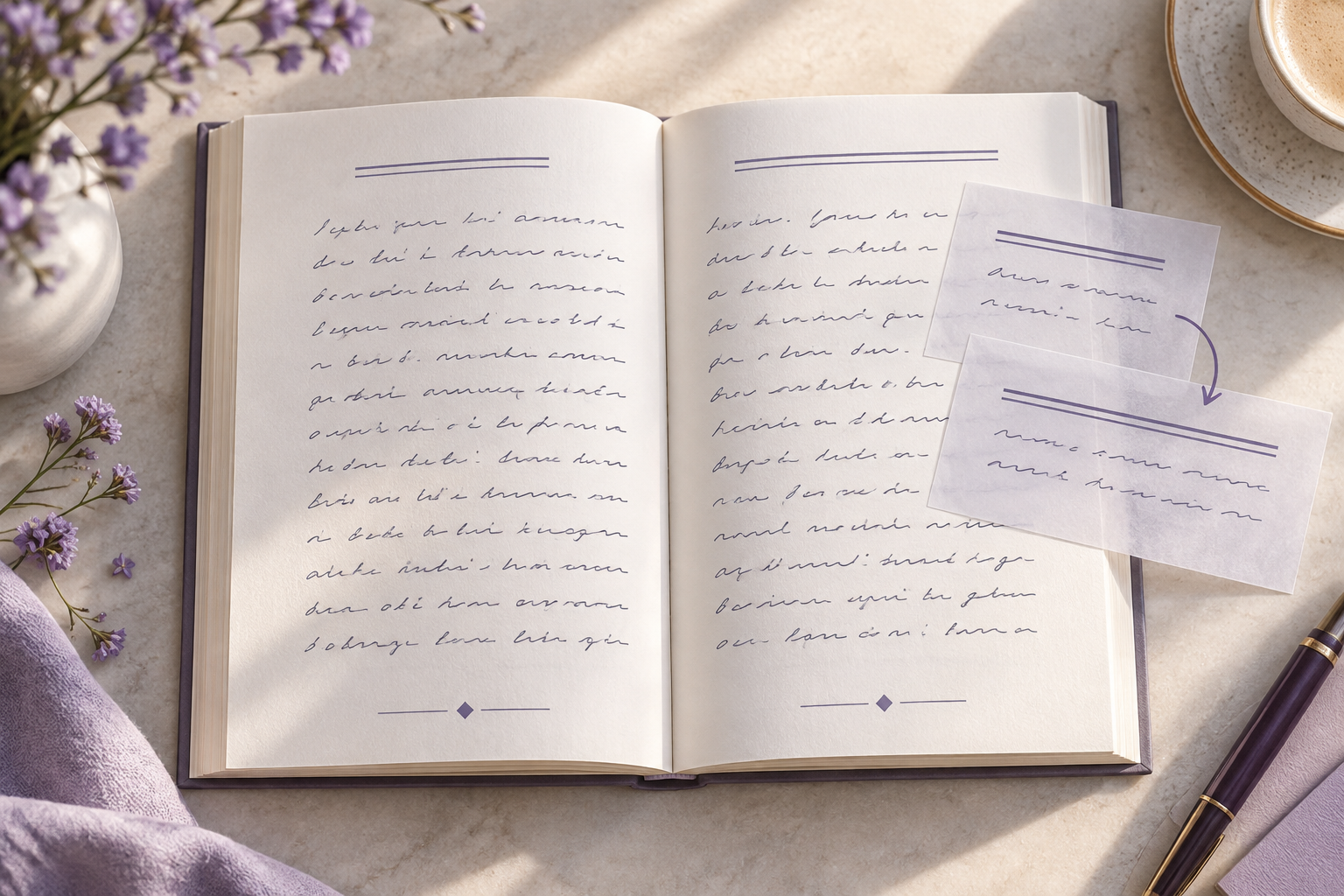
Печатная проба колонтитулов показывает, остаются ли повторяющиеся заголовки и номера страниц заметными, ровными и ненавязчивыми в настоящем книжном развороте. Для проверки нужен не один красивый лист, а короткая последовательность страниц: с длинным и коротким названием главы, сменой чётной и нечётной полосы, переносом и несколькими вариантами номера. Так видно, не теряется ли навигация и не начинает ли шрифт спорить с основным текстом.
Почему колонтитул требует отдельной пробы
Колонтитул — повторяющаяся строка в верхнем или нижнем поле страницы. В нём могут стоять название книги, имя автора, текущая глава или раздел; номер страницы обычно называют колонцифрой. Эти элементы малы и встречаются много раз, поэтому их оценивают не как отдельную надпись, а как часть ритма издания. На экране один заголовок может выглядеть аккуратно, но в серии страниц его ширина, отступы и плотность начинают заметно колебаться.
У рукописного шрифта к этому добавляется неповторимость рисунка. Широкие буквы могут приближаться к внутреннему полю, узкие — оставлять вокруг себя непривычно много воздуха, а росчерки и выносные элементы иногда приближаются к верхней границе. Если набрать один и тот же колонтитул в обычном шрифте-заполнителе, а затем заменить его рукописным, длина строки и зрительный центр могут измениться. Макет при этом формально остаётся прежним, но повтор выглядит неровно.
Отдельная проба полезна до того, как оформлены все главы. Она помогает ответить на практические вопросы: может ли читатель быстро найти номер страницы, не путает ли верхнюю строку с заголовком раздела, остаётся ли название главы в безопасной области и не отвлекает ли повтор на каждой полосе. Это проверка навигации и повторяемости, а не конкурс на самый выразительный колонтитул.
Соберите набор страниц, который выявляет различия
Возьмите отрывок из реального макета или создайте нейтральный тестовый разворот, похожий на будущую книгу. В последовательность стоит включить обычную полосу, начало главы, страницу с длинным названием, страницу с коротким названием, а также чётную и нечётную стороны. Если в проекте предусмотрены пустые страницы или особые полосы без колонтитула, добавьте их как отдельное правило и проверьте переход до и после такой полосы.
Для заголовков выберите несколько строк, различающихся длиной и составом букв. Например, рядом с коротким «Введение» проверьте «Как меняется городская среда зимой». Не подбирайте искусственную фразу только ради набора редких знаков: текст должен быть правдоподобным для книги. Но просмотрите, встречаются ли в названиях широкие буквы, прописные, кавычки или знаки препинания, которые действительно будут в проекте.
Для колонцифр используйте не только номер 1. Проверьте однозначные и двузначные числа, а если книга длинная — также трёхзначное. В рукописном наборе цифры могут заметно различаться по ширине и наклону; цифра «1» иногда выглядит тоньше, чем «8», а «0» может казаться крупнее соседних знаков. Нужна не математическая идеальность, а устойчивое положение номера относительно края страницы и основного набора.
Сохраните один и тот же фрагмент текста и разложите страницы в их реальном порядке. Так можно проверить чередование левого и правого колонтитула и заметить случай, когда длинная строка на одной стороне визуально перетягивает разворот. Если в книге есть несколько шаблонов полос, напечатайте хотя бы по одному образцу каждого шаблона. Один удачный разворот не подтверждает работу всех вариантов.
Настройте образец под будущую книгу
До печати задайте параметры, которые не должны меняться между вариантами: формат страницы, поля, ширину набора, кегль основного текста, положение верхней и нижней границы колонтитула. Если проба нужна для конкретного тиража, используйте бумагу или близкий к ней образец, а также тот способ печати, которым будут получать экземпляры. На другой бумаге и при другом масштабе мелкие буквы могут восприниматься иначе.
В первой версии оставьте колонтитул простым. Выберите один размер, один способ выделения и понятное размещение. Например, автор может стоять слева на чётной странице, а название раздела — справа на нечётной; номер страницы останется ближе к внешнему нижнему краю. Это только один из вариантов, а не обязательная схема. Важно, чтобы правило читалось на развороте и сохранялось на протяжении книги.
Рукописный шрифт может иметь неравномерную ширину знаков. Поэтому не ориентируйтесь только на центрирование рамки в программе. Посмотрите, как строка воспринимается на бумаге относительно поля, соседней полосы и основного текста. Иногда длинный заголовок полезно ограничить отдельной шириной или уменьшить на один шаг, но сначала убедитесь, что читатель всё ещё распознаёт его без усилий.
Если заголовок не помещается, не сжимайте его по горизонтали автоматически. Такое преобразование может сделать штрихи непривычно узкими и нарушить характер букв. Сначала сократите формулировку, перенесите её на вторую строку, уменьшите кегль в заранее установленном пределе или исключите текущий заголовок только на этой странице. Выберите один подход и протестируйте его на самом длинном реальном названии.
Проба колонтитулов оценивает не одну удачную строку, а систему повторов: как меняются заголовки, номера и поля на последовательности реальных страниц. Подготовьте несколько репрезентативных полос, напечатайте их в нужном масштабе, просмотрите отдельно и в развороте, а затем вносите по одной измеримой правке. Создайте рукописное начертание в Fontgenerator и используйте тот же набор страниц, чтобы проверить его в будущей книге.